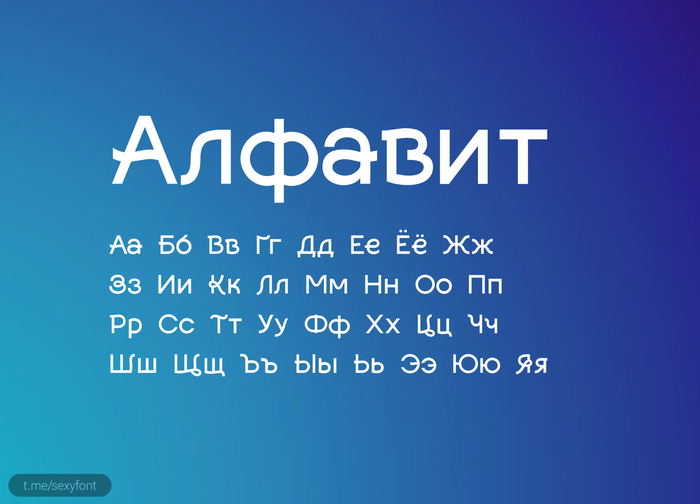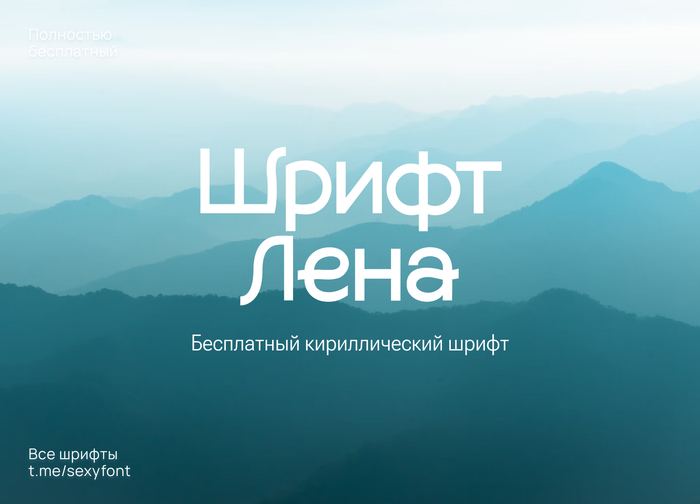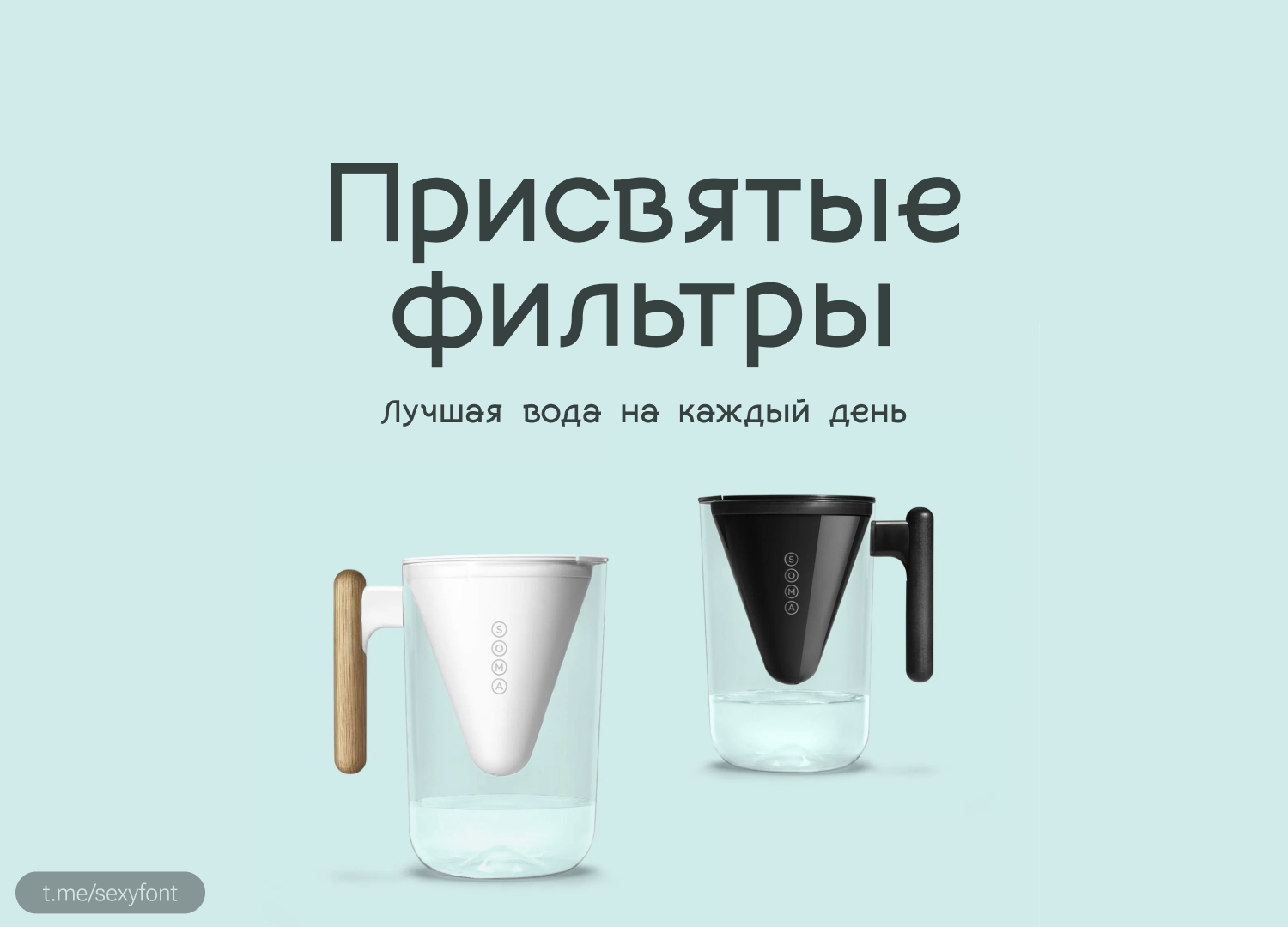
Шрифт Лена
Бесплатный, кириллический. Я написал автору и уточнил. Красивые волнистые буквы идеально подойдут под многие темы. Пользуйся. Автор шрифта: Vsevolod Abramov